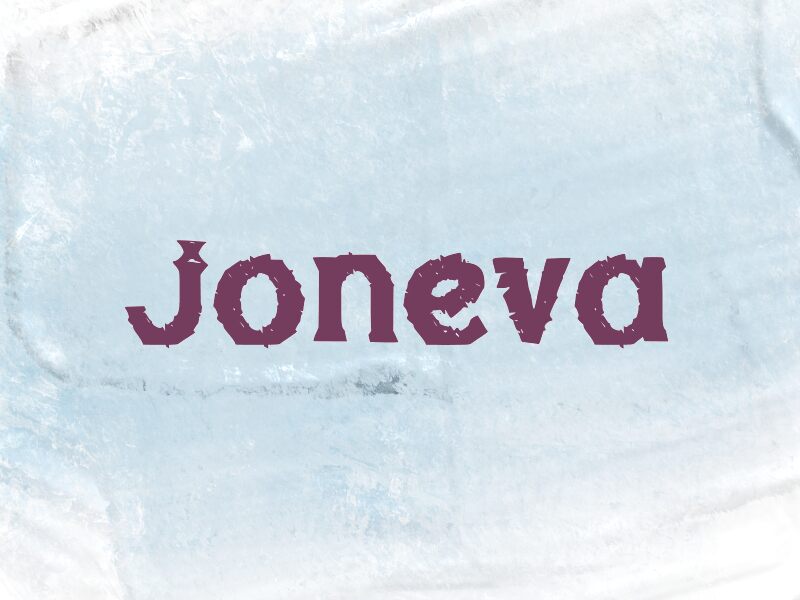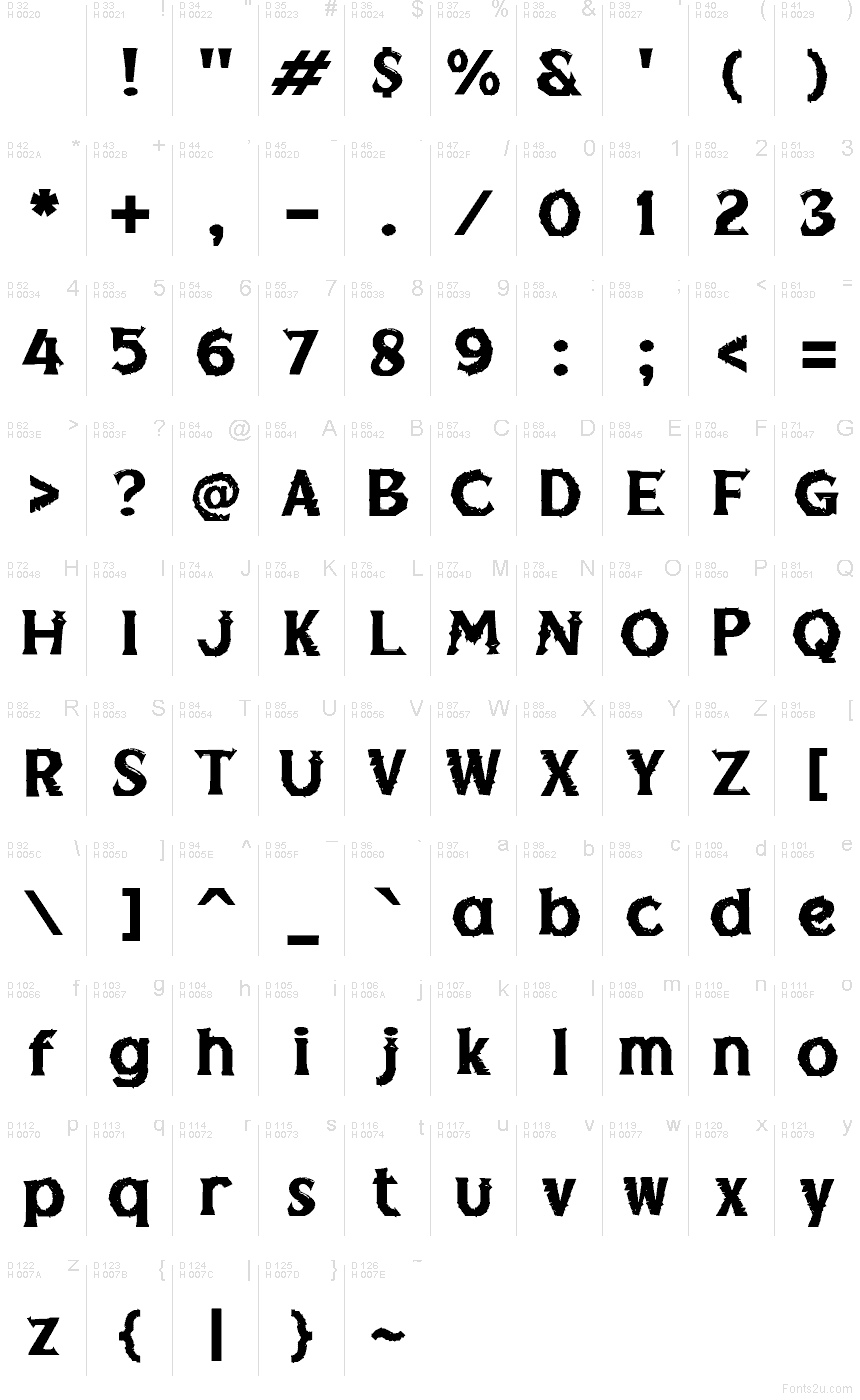
Joneva
Joneva od Wep je bezplatné displejové písmo s erodovaným vzhľadom, ktoré formujú drsné, potrhané okraje a vyryté plochy. Vďaka nim pôsobí každé písmeno ako vyrezané, odštiepené a mierne nestabilné. Táto drsná textúra prestupuje celý dizajn a dodáva písmu výrazný, plagátový charakter, ktorý ďaleko presahuje bežné povrchové ošúchanie.
Je ideálne na hororové titulky, letáky undergroundovej hudby, náhľady hier, plagáty na akcie a merchandisingovú grafiku, kde poškodený povrch pomáha dotvárať náladu. Najlepšie vynikne v krátkych nadpisoch a logách, pretože široké tvary držia celok pokope, zatiaľ čo rozbité obrysy bránia tomu, aby písmo pôsobilo plocho alebo genericky.